Renor Curioso y Gemma O’Brien
Algunos tipos de letras nos gustan más que otros y esto se debe simplemente porque nos sentimos inconscientemente identificados con la forma de sus trazos, el cerebro se identificara mejor con aquello que le es familiar, la letra refleja nuestra personalidad y cuando estamos frente a algo similar a nosotros esto es aceptable más fácilmente por nuestro cerebro. La grafología a través de años de investigación y análisis es la encargada de mostrarte la compatibilidad que existe entre la letra y tu personalidad.
“Es el cerebro el que escribe. El brazo, la mano, los dedos no constituyen los verdaderos factores de las peculiaridades esenciales e individuales de la escritura”.
Max Pulver. Grafólogo y psicólogo suizo.
Cuando se nos presenta una letra inevitablemente nuestro cerebro la calificara de bonita o fea según sean nuestros gustos, aunque para la grafología se calificarán en legibles e ilegibles. Lo primero que llamará nuestra atención será la forma de lo cual dependerá en que simpaticemos o no con dicha letra, para lo cual tendremos que distinguir los dos grandes grupos de la forma que son: los trazos curvos y los trazos angulosos, cada uno con sus propias variantes.
Entendiendo por trazo curvo todo aquel que tiene una trayectoria que gira en su propio eje formando círculos, semicírculos, espirales etc. Dentro de los trazos curvos encontramos los llamados “bucles”, que son aquellos trazos curvos que giran en forma de coquetos y seductores rizos de ciertas escrituras.
Gemma O’Brien
Si a ti te agradan las imágenes con bucles y puedes trazarlos con gran naturalidad es porque tienes facilidad y encanto al hablar, habilidad que podrías desarrollar si te gustan las ventas, nadie podrá resistirse a tus encantos porque además eres simpático y amable. Los bucles revelan tu capacidad de adaptación para poder aprovechar cada situación a tu favor, y si, también revelan tu grado de egocentrismo, a más bucles mayor egocentrismo.
Jaime De Albarracín
Pero cuando estos bucles se enrollan para juguetear y unirse con otros bucles se llamarán “lazos”. Los lazos son muy recurrentes en las zonas bajas de la escritura, mostrando la habilidad manual, la coquetería y el lado seductor de quien así escribe. Son personas con facilidades para la decoración. Tu gran capacidad para enrollar esos trazos será la misma que te ayudará a convencer a los demás de que hagan lo que necesites para lograr tus objetivos personales. Eres vanidoso y un tanto egoísta, te encanta dejar expectación y misterio en las personas que te conocen.
Para la grafología el ángulo es aquel trazo recto o puntiagudo que se presenta donde por naturaleza debería haber una curva en la escritura, por ejemplo cuando encontramos vocales no tan redonditas. Pero ahora no hablaremos de las letras, sino de los trazos finales, el modo peculiar de trazar esa última línea antes de levantar el útil inscriptor.
Cuando los finales de tus trazos son de modo grueso, iniciando con un trazo delgado que irá ganando grosor mientras avanza su trayectoria cargando de tinta solo la zona final dando una forma cuadrada a la punta, como lo observamos en las barras de la “t” en la siguiente imagen.
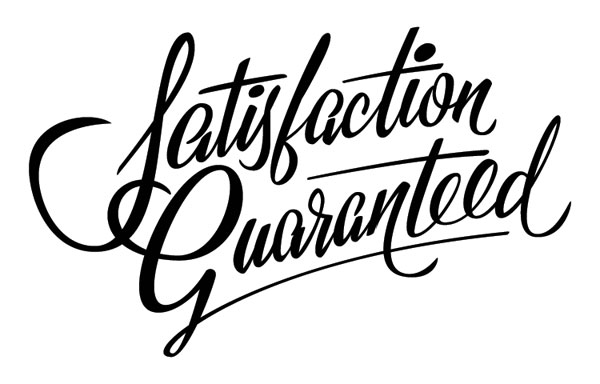
James T Edmondson
Esto es indicio de energía propia de personas activas, decididas y apasionadas que prefieren tener el control de la situación antes que tener que adaptarse a ella, por lo que son verdaderamente audaces para imponer sus propias ideas. Esta acumulación de tinta también nos revela una buena capacidad para tomar decisiones y poner en marcha proyectos que a pesar de encontrar ciertas dificultades siempre logran vencer los obstáculos con energía.
Otro tipo de ángulo es en forma triangular cargado de tinta en su zona inicial terminando en un trazo delgado y con punta fina en forma de aguja. Este tipo de trazo es característico de personas con una gran agilidad mental para defenderse, atacar o replicar cualquier cosa en tono irónico, les gusta ser sarcásticos, son observadores y algunas veces mal pensados. Les gusta la independencia, suelen ser nerviosos y dominantes. Y como es muy característico de los angulosos, también prefieren imponer sus propias ideas a los demás.
Nicolas Rojas
Cuando los trazos se inclinan hacia la izquierda, si la escritura tiene un aspecto comprimido, con poco espacio entre las letras que forman cada palabra y prevalecen las angulosidades estamos frente a una persona precavida que preferirá ser desconfiado antes que arriesgarse a perder. Prefieren trabajar de forma independiente o solo pues el contacto social no es algo que le interese mucho. Son introvertidos, susceptibles, malhumorados y difícilmente olvidan o perdonan las ofensas.
Evgeny Tkhorzhevsky
El contraste que provocan los trazos gruesos y finos da un aspecto a la imagen de relieve. Provocando un balance armonioso y estético agradable a la vista.
Son personas con buena energía que están siempre en busca de avanzar pues no les gusta el estancamiento. Desconfiados y precavidos. Prácticos por naturaleza, pero siempre son muy críticos y selectivos lo que los pudiera hacer parecer complicados, quisquillosos y un tanto obsesivos. Son tan exigentes y meticulosos consigo mismo como lo son con los demás. Algunas veces polémicos.
La escritura de trazos gruesos con abundante carga de tinta realizadas a mano ya sea con pincel o rotulador son calificadas de escritura espesa, aunque también tomaremos como espesas aquellas diseñadas con ayuda digital para dar dicho efecto.
José Luis Vivas (Joluvian)
Estas formas gruesas y de abundancia de tinta son muy bien aceptadas por personas que aman y disfrutan al máximo la vida, les encantan los lujos y placeres terrenales. Son eufóricos y con una gran imaginación. Como pareja suelen ser muy intensos y algunas veces difíciles. Su gran necesidad de satisfacer los placeres físicos suelen arrastrarlos hacia las infidelidades.
Alan Guzmán
Las descripciones que he dado son en referencia a los gestos gráficos señalados de las imágenes presentadas. Cada artista realizara una gran variedad de trabajos a lo largo de su carrera, desarrollando la habilidad para ejecutar la imagen que se le pide crear para identificar a cada cliente. Aun así, cada artista tendrá predilección o facilidad por ciertas tendencias de trazado, la cual será su sello personal. Su firma.
“La firma es una biografía abreviada”.
Max Pulver.
“Tu letra me dijo todo lo que
tú no pudiste platicarme”.
Karina Rivas Palafox.